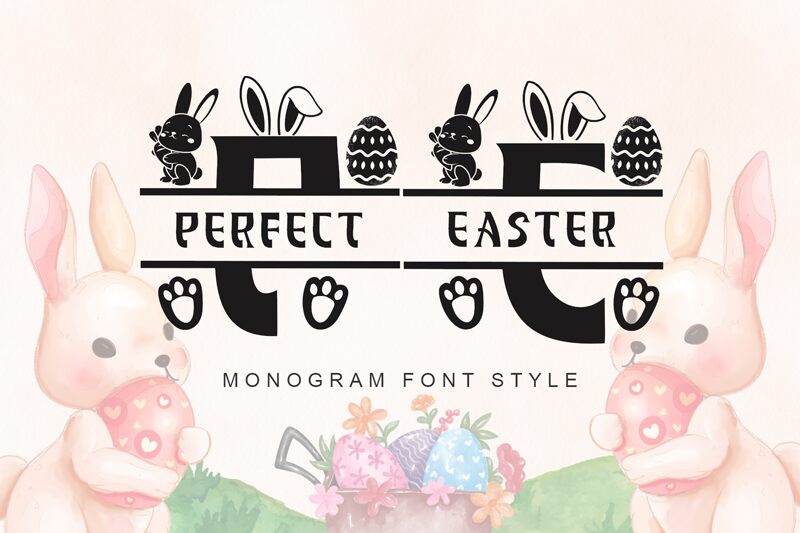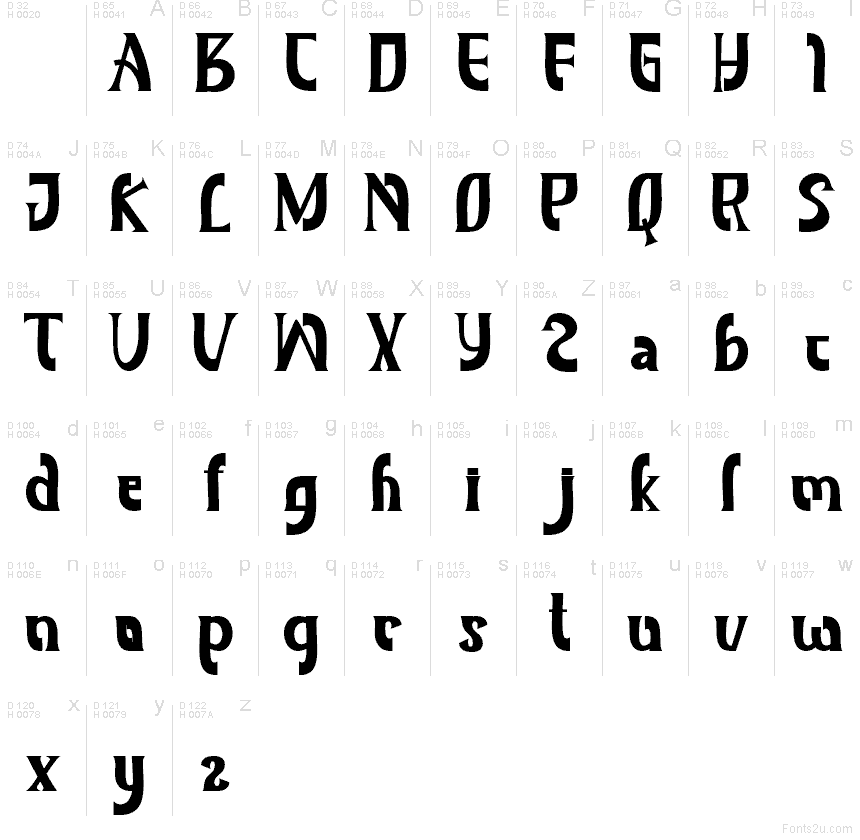
Perfect Easter Demo
Perfect Easter par Yoga Letter est une police d'affichage gratuite pour Pâques. Avec ses formes arrondies et massives façon « découpage », elle évoque l'esthétique des banderoles artisanales. Ses caractères larges et compacts, mêlant courbes douces et angles droits, offrent une belle souplesse visuelle sans jamais paraître rigides.
Perfect Easter Demo fonctionne à merveille pour des cartes de Pâques, des visuels de soldes printanières, des affiches de fêtes, des invitations ou des étiquettes saisonnières, là où une police thématique doit rester joyeuse sans fioritures excessives. Cette police gratuite est également idéale pour le packaging artisanal, les en-têtes de réseaux sociaux et la signalétique décorative, car ses formes solides conservent toute leur lisibilité dans les mises en page larges et percutantes.